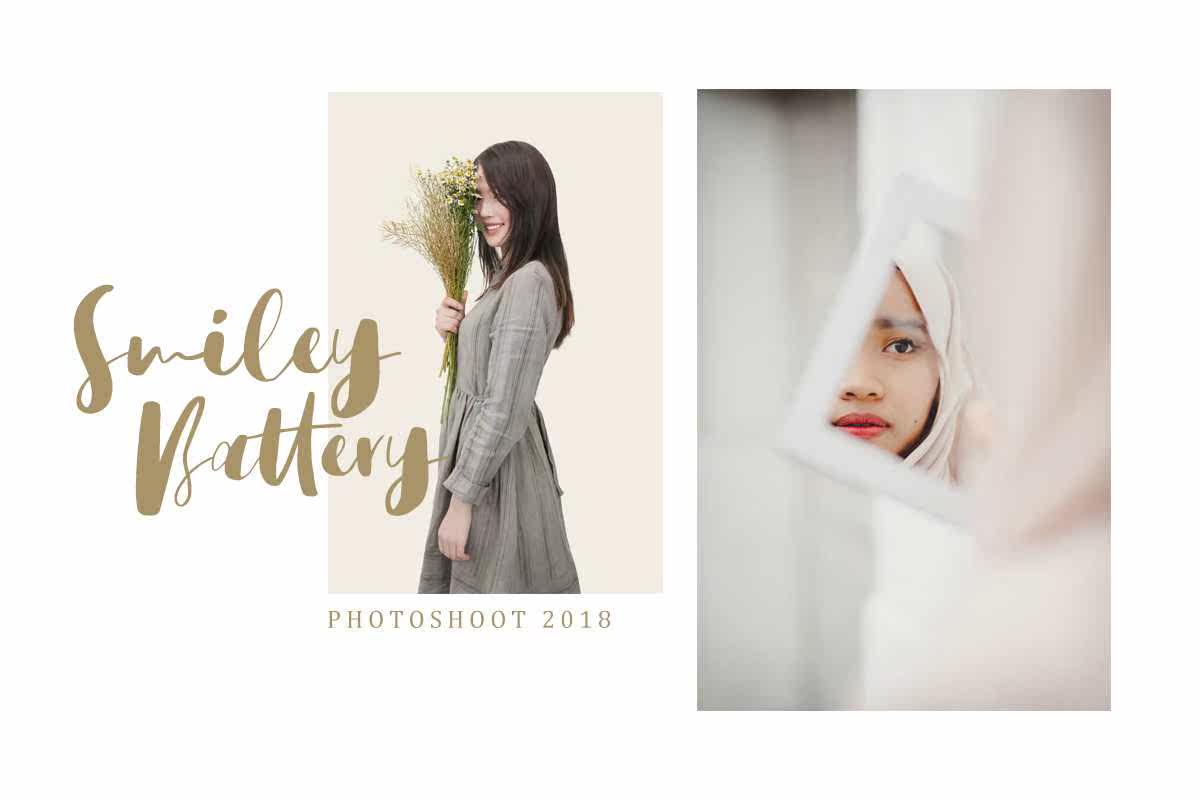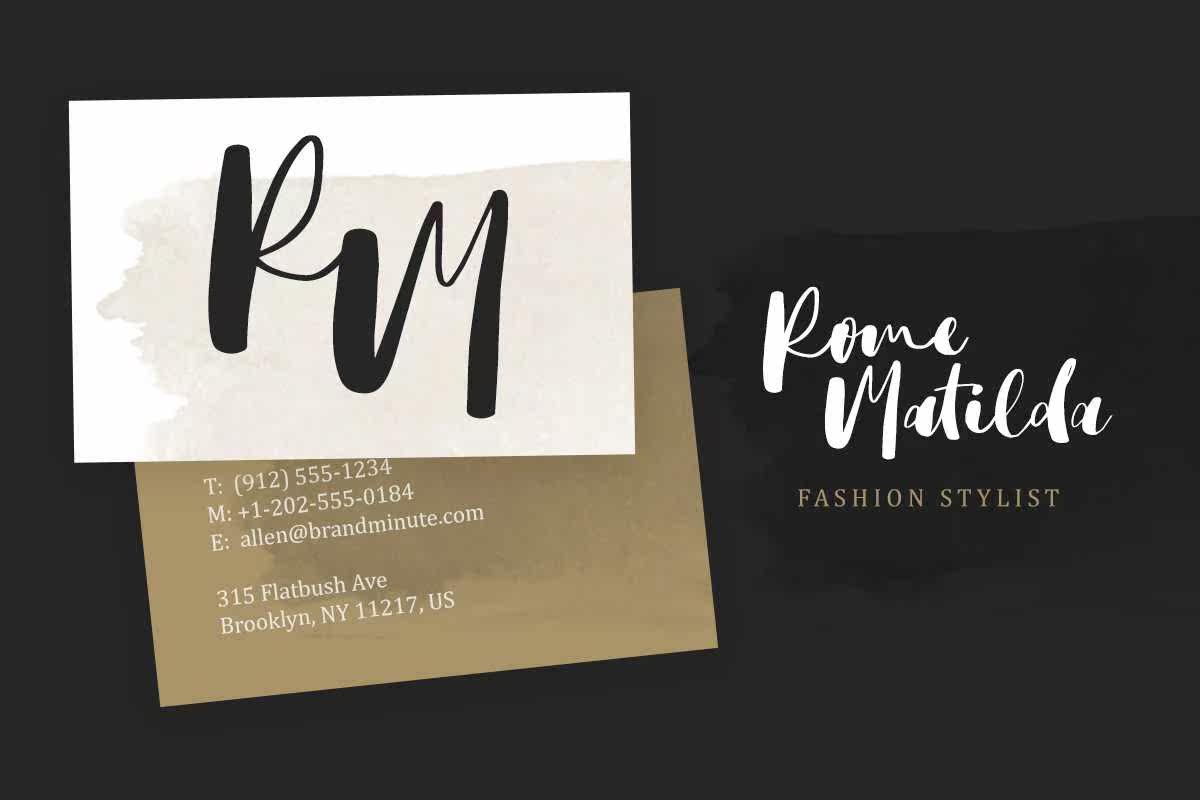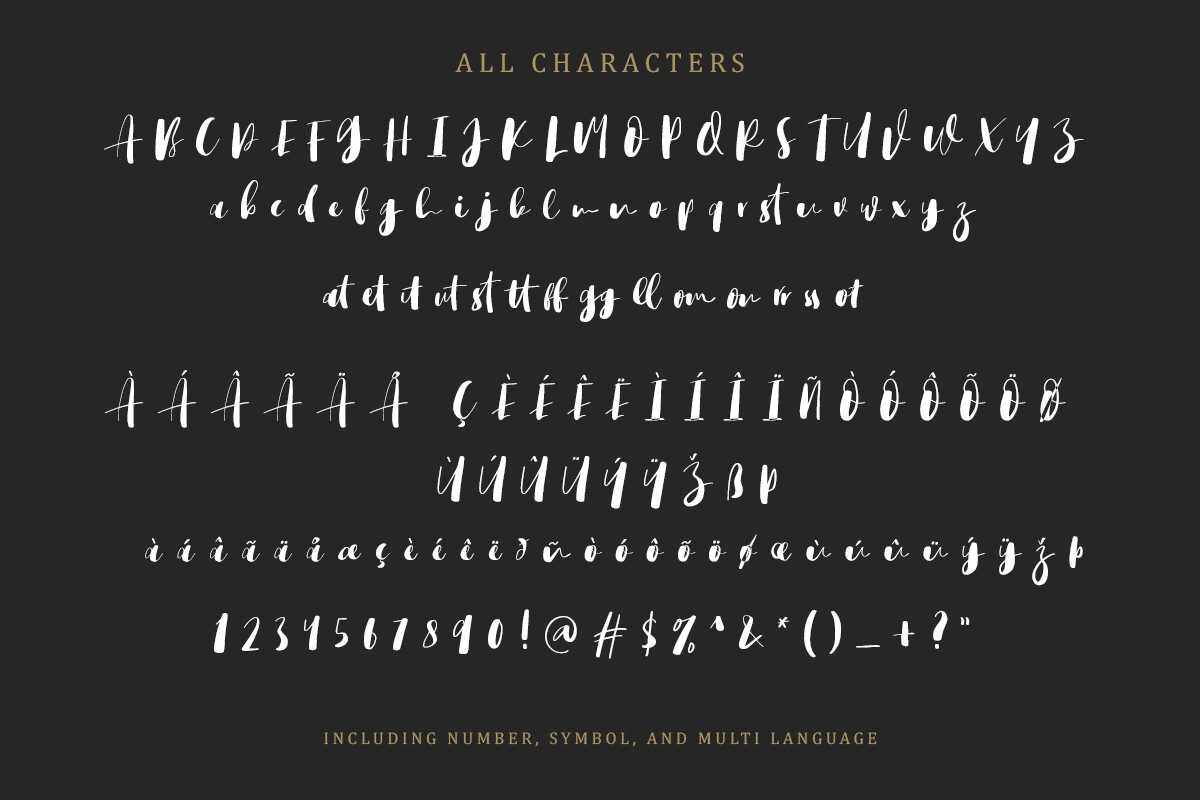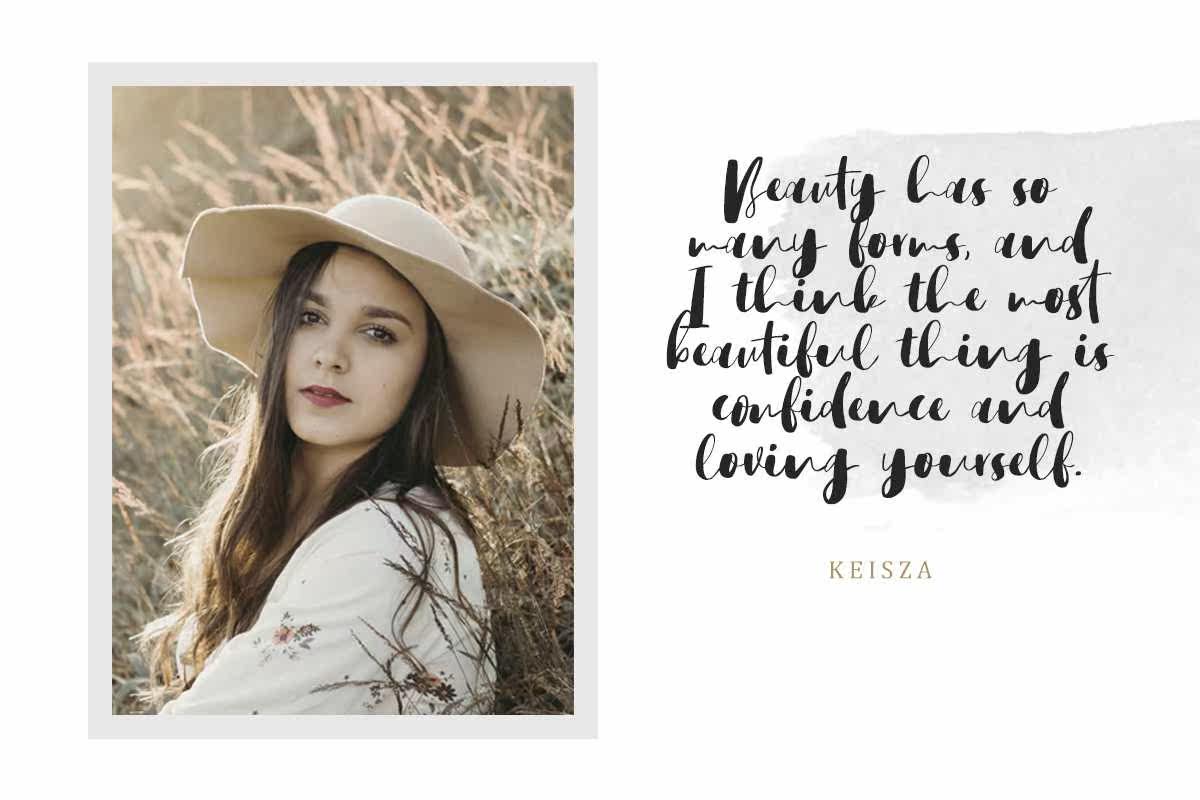
Bigstorm是一款独特的手工设计,它将捕捉人物的注意力。该字体适用于签名、标题、文字引用、婚礼宣传、时尚等。它还包括大写字母、小写字母、标点符号、符号和数字、文体设置、替换字母、连字、,EtcalSo支持多语言。BigStorm是一款独特的手工字体,将捕获Tentitation Lance。此字体适用于签名、标题、文字引用、婚礼宣传、时尚等。它还包括大写、小写、标点符号、符号和数字、文体设置替换、连字等,支持多语言。